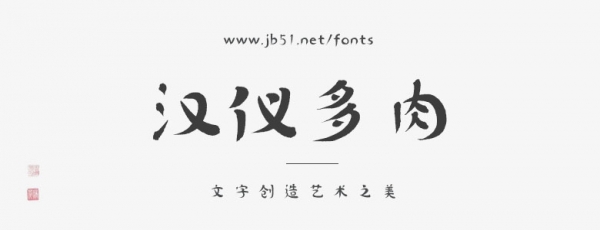
漢儀多肉是由青年書法家李揮毫創(chuàng)作的一款創(chuàng)意書寫字體,整體設計取多肉植物的形態(tài),風格自然,包含溫柔細膩的情感。這款字體適合清新浪漫的使用場景,可用作標題字體。
不同文字的形態(tài)能帶給人很多感受,個人感覺這款字體更適合寫情書使用,比較小清新。多肉植物頑強堅韌,又寓意愛情的永恒,所以就取了這個名字。——來自作者李揮毫的一段話